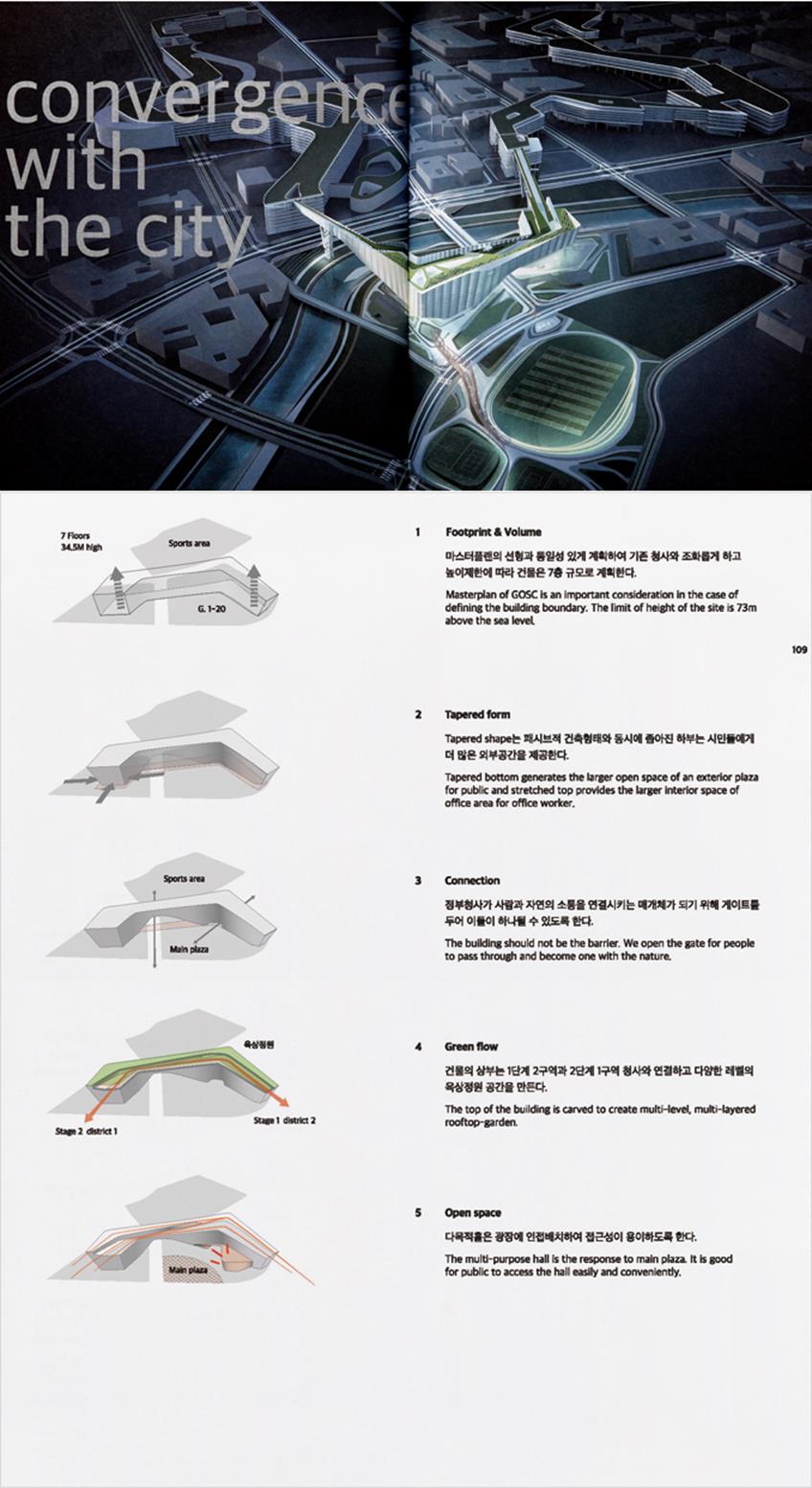
산돌네오시리즈_4.디자이너 리뷰_폰트 사용기
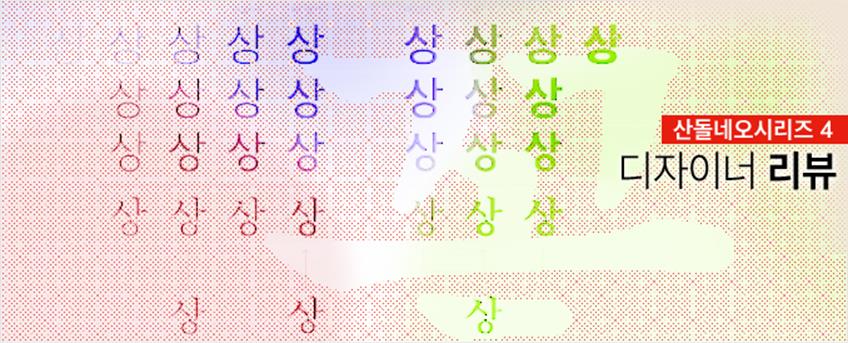
“가려운 부분도 긁어주고, 수고도 덜어준 폰트”
섬세한 디자인 작업을 할 때면 폰트가 조금만 더 굵었으면, 조금만 더 가늘었으면 하는 아쉬움이 생기곤 한다. 산돌고딕네오는 바로 이러한 디자이너의 가려움(?)을 긁어주기 위해 탄생한 폰트처럼 여타 한글 폰트에서 볼 수 없었던 아홉 개의 웨이트로 이루어진 패밀리를 갖고 있다. 아마도 네오고딕의 가장 큰 장점이 아닌가 싶다. 알파벳이 세련되지 않은 기존 한글 폰트 때문에 한영 타이포그래피 작업 시 알파벳 부분을 영문 폰트로 바꿔 사용하는 경우가 많은데, 이는 편집 디자이너로서의 당연한 수고이자 번거로움이다
산돌네오시리즈는 이러한 디자이너의 수고를 덜어주고자 Guardians를 라이선스로 받아들인 것 같다. 지금까지 한글 고딕과 조합해서 Helvetica, Univers, Din 등을 주로 사용했던 경험 때문에 산돌고딕네오의 한영 조합이 다소 어색하게 느껴지기도 하지만, 이 부분은 탈네모꼴 글자를 처음 접했을 때의 생경함처럼 작업을 반복할수록 조금씩 사라질 것으로 보인다. 디자이너와 함께 고민하고 이를 해결하고자 노력하는 산돌에 열의에 박수를 보낸다.
디자인네트 특집
디자인 | 박민수
월간 <Designnet> 2월호 특집에 산돌네오시리즈를 적용해 보았다. 장표지 제목에서 다양한 웨이트를 가진 고딕네오의 장점을 살렸다. 한글과 영어가 섞인 본문에 다른 종류의 한글과 영문 폰트를 쓰지 않고 제목과 본문에 모두 고딕네오만을 사용했다. 고른 회색도를 이루어 안정적이고 깔끔한 느낌을 살릴 수 있었다.
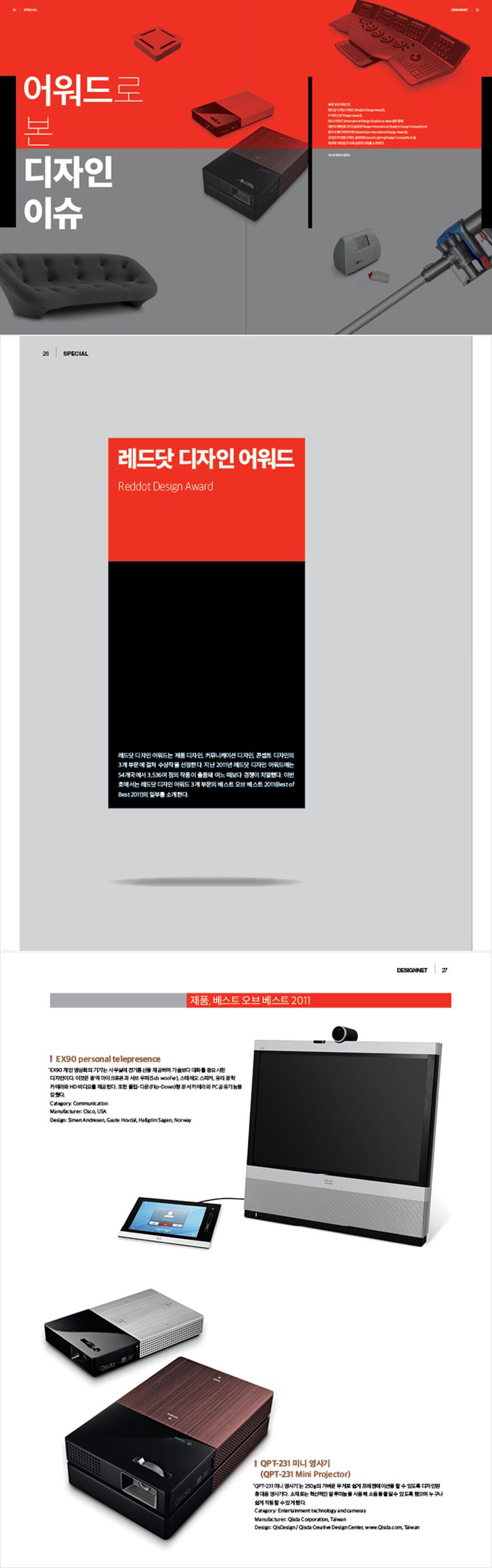
“필요했지만 없었던, 새로운 시대가 요구하는 폰트”
시장에는 이미 적지 않은 한글 폰트가 출시되어 있다. 새로운 폰트도 계속 발표되고 있으며 조금씩 한글 폰트 인프라도 확장되고 있다. 그 중에서 네오고딕은’필요했으나 없었던 포지션’의 폰트이다. 고딕네오은 iOS5에 탑재되면서 ‘On Screen’ 폰트로서의 가능성을 보여줌과 동시에 기존의 옵셋 인쇄에도 유연하게 대응하고 있다는 점에서 특히 그러하다. 물론 iOS에는 수십 종의 다른 문자와 섞어 써야 하는 등, 여러 가지 제약으로 인해 고딕네오의 한글만 사용되었으나 역설적으로 얘기하면 이 또한 거스르기 힘든 국제적인 흐름이기도 하다.
새로운 시대가 요구하는’폰트 패밀리’의 역할은, 다양한 웨이트 지원뿐 아니라, 그것 하나만으로도 일관성 있는 디자인 아이덴티티와 퀄리티를 보장할 수 있어야 한다는 점이다. 즉 앞으로의 디자인 결과물은 매체의 종류가 바뀌더라도 퀄리티가 유지되어야 한다. 산돌의 네오시리즈는 이 점에서 우위를 보이고 있으며, 앞으로 종이와 화면의 경계를 허무는 선도적인 역할을 해나가길 바란다.
SBI 2012 교육생 자료집
디자인ㅣ고영선, 유진아(SBI 북디자인 과정)
현재 SBI(Seoul Book Institute, www.sbin.or.kr)에는 북에디터, 북디자이너, 북마케터 교육과정이 6개월 코스로 개설되어 있다. 그 중 북디자이너 코스 학생들이 본 교육 과정의 취지와 결과물을 책으로 엮는 프로젝트를 진행하였다. 학생들이 기획부터 디자인까지 모두 진행하는 다소 어려운 프로젝트였고 일정 또한 매우 촉박하였다. 이럴 때일수록 타이포그래피의 디테일에 신경 쓸 여유는 더더욱 없다. 그래서 학생들에게 산돌고딕네오1을 추천하였고 촉박한 일정 속에서도 만족할 만한 결과를 얻을 수 있었다.
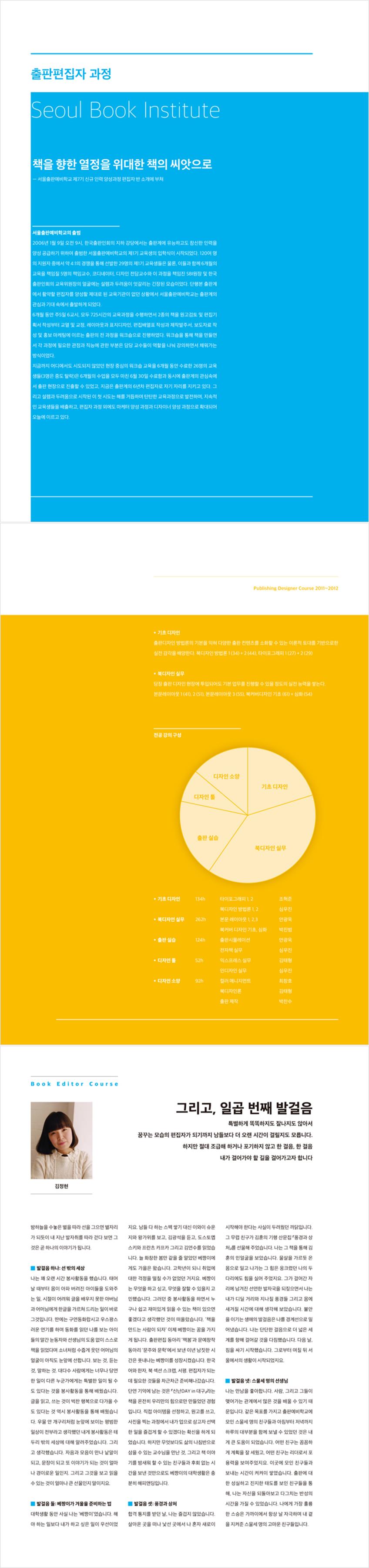
“효과적인 메시지 전달과 독자만족을 가능하게 해 준 폰트”
<스티브 잡스> 전자책의 가장 큰 매력은 서체, 정확히 말하면 산돌명조네오를 활용해 완성한 본문 디자인이다. <스티브 잡스> 전자책이 제작되던 당시, 국내에서 유통되는 단행본 전자책에 폰트를 내장한 사례는 찾아보기 어려웠다. 폰트를 내장해 전자책을 만든다는 것 자체가 하나의 도전이었다. 하지만 산돌명조네오가 있어 그 도전이 가능했다.
산돌네오시리즈는 기존 종이책에서 사용하던 서체에 비해, ㅁ, ㅇ의 속공간이 커서 전체적으로 젊은 느낌을 주고, 다른 전자책 서체와는 달리 글자들의 위 선이 고르게 맞는다는 강점이 있었다. 글줄 형성이 확실한 점은 전자책 독서의 가독성을 높일 수 있는 중요한 요소이기 때문에 특히 중요하게 고려하는 부분이다. 전각기호나 라틴 알파벳 서체 스타일이 잘 잡혀 있다는 점도 작업을 용이하게 해주는 중요한 부분이다. 그 점에 있어서는 <스티브 잡스> 종이책 표지에 사용되면서 애플의 디자인 철학을 가장 잘 반영한 서체로 회자되기 시작한 산돌고딕네오 또한 마찬가지다.
<스티브 잡스> 전자책과 종이책 모두 산돌네오시리즈를 활용함으로써 효과적인 메시지 전달과 독자 만족이라는 두 마리 토끼를 잡는 일이 가능하지 않았을까?
<스티브 잡스> 전자책
폰트는 독자들의 독서 체험에서 가독성이나 눈의 피로도와 밀접하게 연관된 가장 중요한 요소다. 전자책 편집에 적용하는 대부분의 고딕체 계열은 오랜 시간 읽게 되면 눈을 피로하게 만들기 때문에 <스티브 잡스> 처럼 분량이 많은 책에서는 명조체 계열의 폰트 도입이 가장 중요한 이슈 중 하나였다. 따라서 전자책에 적용할 적당한 한글 전용 폰트를 찾는 데 오랜 시간이 소요되었고, 결국 민음사는 산돌커뮤니케이션의 협조 아래 산돌고딕네오와 산돌명조네오를 전자책 <스티브 잡스> 내장 폰트로 사용할 수 있었다.
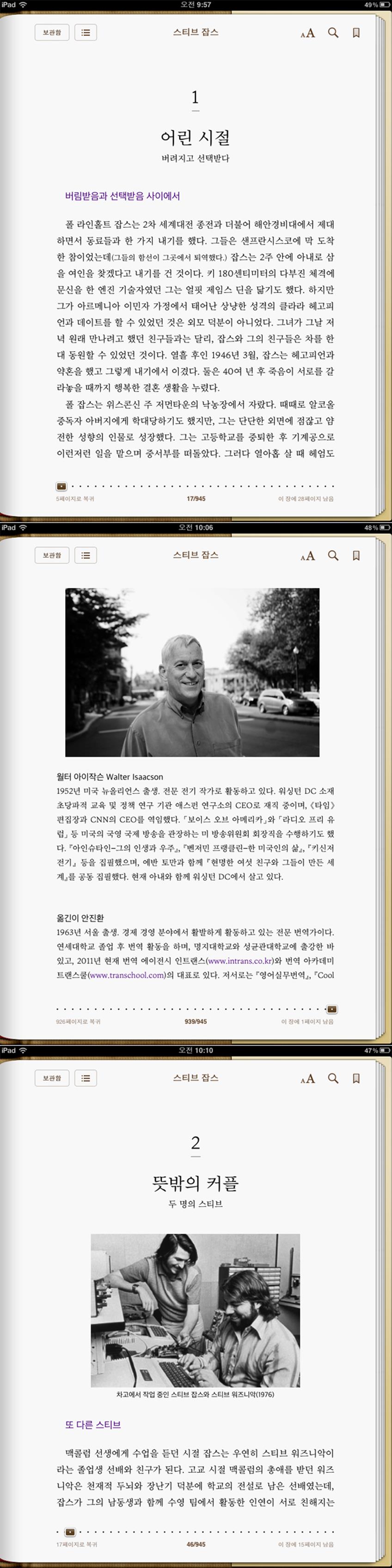
“디자이너의 공기를 정화해준, 묵묵한 노력의 결과물”
갓난아이가 처음 말을 배울 때처럼 디자이너가 서체를 다룬다는 것은 커뮤니케이션의 가장 기본 요소를 어떻게 활용할지를 판가름하는 첫걸음일 것이다. 그 중에서도 우리가 공기처럼 호흡하고 있는 명조와 고딕 서체의 중요성은 두말할 나위가 없다. 하지만 경제논리에 휘둘려 단조로운 환경 안에서 불편한 선택을 해왔던 것 또한 사실이다. 숨 쉬고 있는 공기가 좋지 않다는 것은 누구나 알지만, 정화를 위한 ‘티’가 나지 않는 이 묵묵한 노력의 결과물인 산돌네오시리즈는 그래서 더욱 가치 있는 일일 것이며 이를 토대로 산돌네오시리즈가 우리나라 디자인의 기본을 조금이나마 바르게 흔들어 놓을 만큼의 사건으로 기억된다면 좋겠다. 한글 특성상 워낙 방대한 조합이라 모든 면이 완벽할 수는 없겠지만 이를 계기로 우리의 공기가 한결 숨쉬기 편해지고 신선해졌다는 사실은 매우 고무적이며, ‘사실’일 것이다.
토문 세종시 아트북
디자인ㅣ이상윤
토문건축사사무소(www.tomoon.co.kr)의 세종시 정부청사 설계 아트북을 산돌네오시리즈로 작업하였다 합성글꼴이나 섬세한 서체 설정을 따로 하지 않고도 미려한 결과물을 얻을 수 있었다. 이는 모든 사용자가 큰 수고로움 없이 상향 평준화된 결과물을 얻을 수 있는 서체 자체의 놀라운 힘을 의미한다. 그리고 산돌네오시리즈의 가장 큰 장점 중 하나인 영문 서체의 라이선스 도입은 사용자에게 있어 신뢰감을 주었고 더불어 한글과의 균형감도 유연하게 잘 유지할 수 있게 했다. 따라서 한영 병행 제작물에서 크게 고민하게 되는 두 언어 간의 조합 문제를 일부분 해소된 것으로 보이며, 영문 서체가 주는 오리지널리티 느낌을 그대로 전달하면서도 회색도가 균형감을 갖는 것이 가장 큰 장점이었다. 다만 두 언어의 근본적 차이지만 상호 크기의 불균형, 그리고 헬베티카와 같은 고딕체에 익숙해진 우리 눈에 어색함이 아닌 신선한 어울림으로 다가올지는 좀 더 지켜볼 일이다.